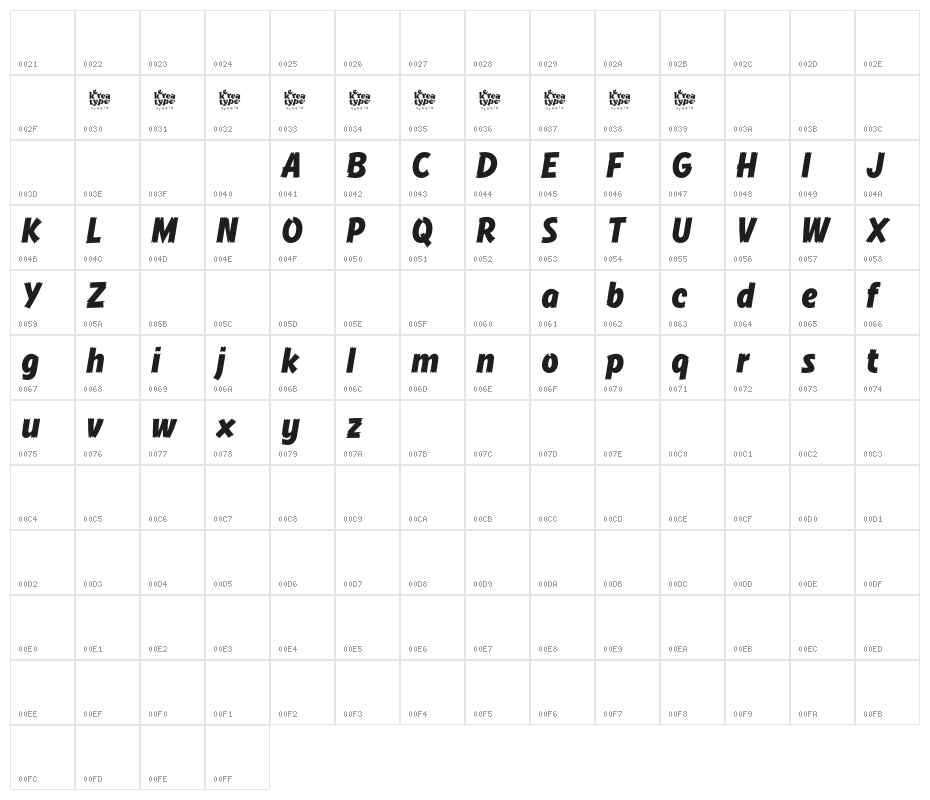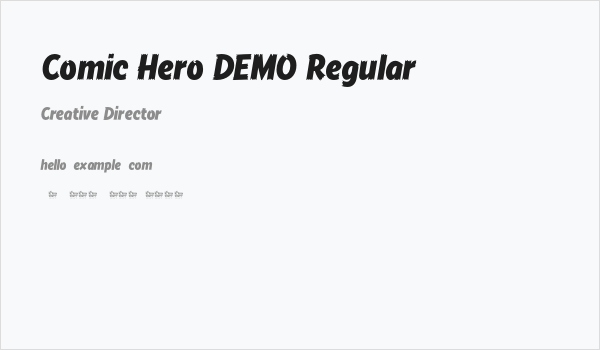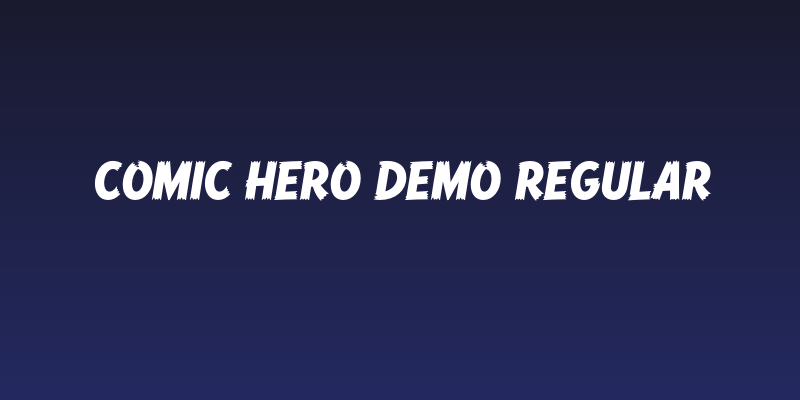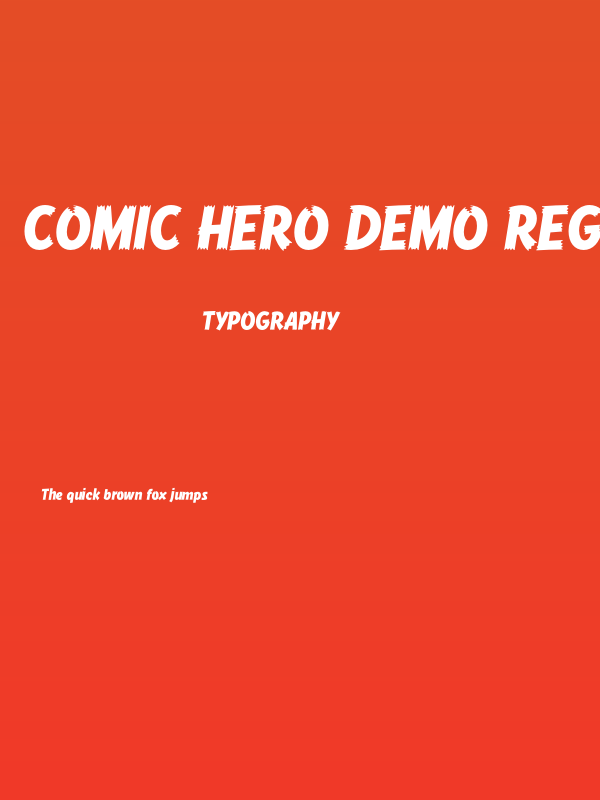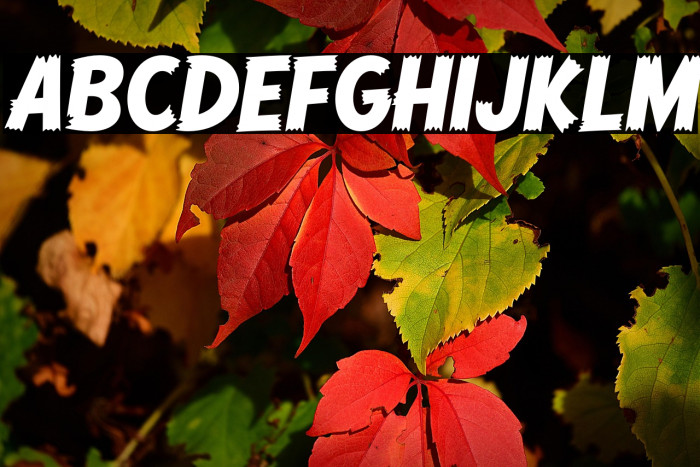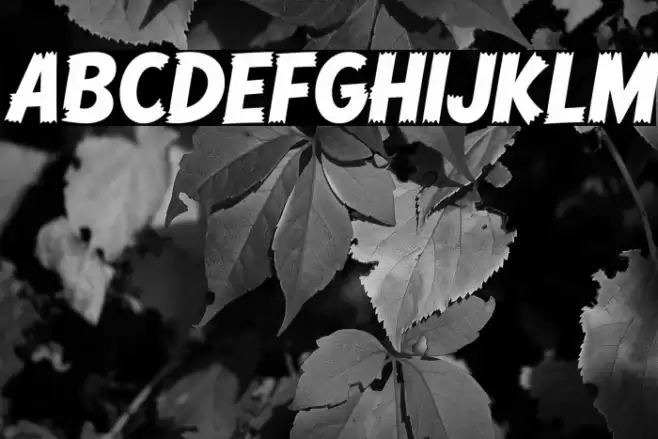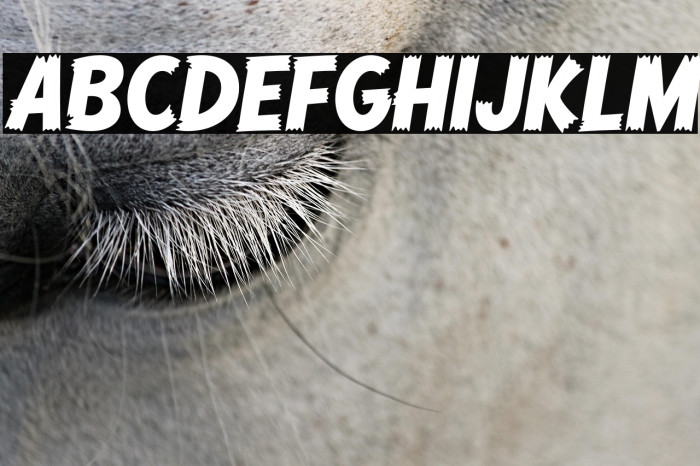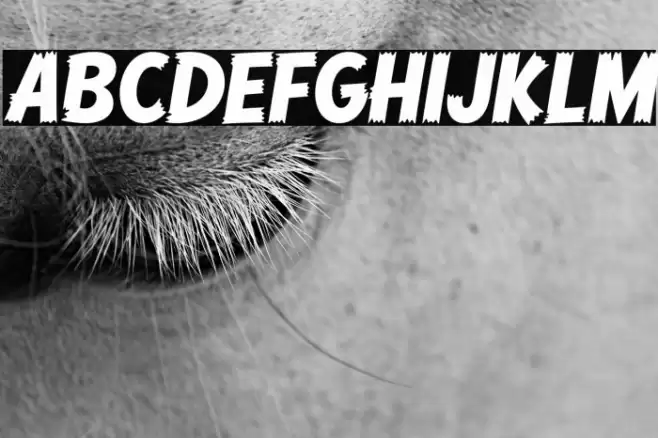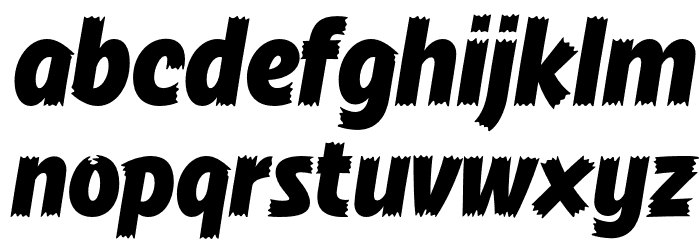
Comic Hero DEMO Regular Font
| Gesamtstil | Playful, Energetic, Comic |
| Anwendungsfall | Headlines, Posters, Branding |
| Vorgeschlagene Projekte | Ideal for comic books, children's books, posters, and playful branding. |